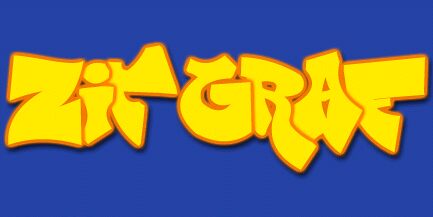
Zit Graffiti od Zitfonts to darmowy krój graffiti z niezobowiązującym klimatem ulicznych tagów z początku XXI wieku. Litery sprawiają wrażenie spuchniętych, powykrzywianych i lekko nierównych, a mieszanka pełnych kształtów z konturowymi nadaje całości improwizowany, śmiały i nieco niepokorny wyraz.
Idealnie pasuje do plakatów, grafik na mixtape’y czy klubowe ulotki, brandingu skate, streetwearu i napisów, gdzie sztywna siatka wydawałaby się zbyt nudna. Jako darmowy font sprawdzi się też w krótkich nagłówkach, ponieważ masywne sylwetki i nagłe krzywizny dodają nawet kilku literom dynamiki ręcznie malowanego napisu.